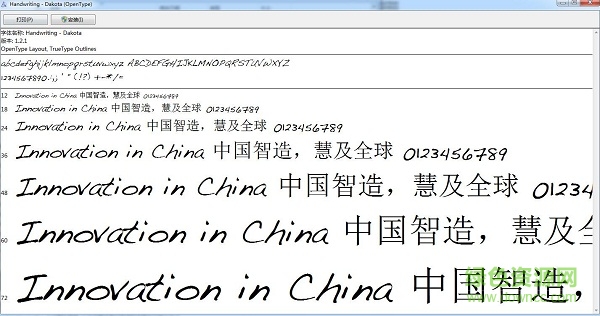
handwriting-dakota字體是一款讓人賞心悅目的英文手寫字體,字體線條飛揚(yáng),俊秀美觀,風(fēng)格鮮明,適用于包裝設(shè)計(jì)、詩(shī)歌排版以及文化主題的廣告設(shè)計(jì)!
具有較強(qiáng)的現(xiàn)代氣息,風(fēng)格飄逸靈動(dòng),適用于商業(yè)類品牌的廣告語設(shè)計(jì),百看不厭!